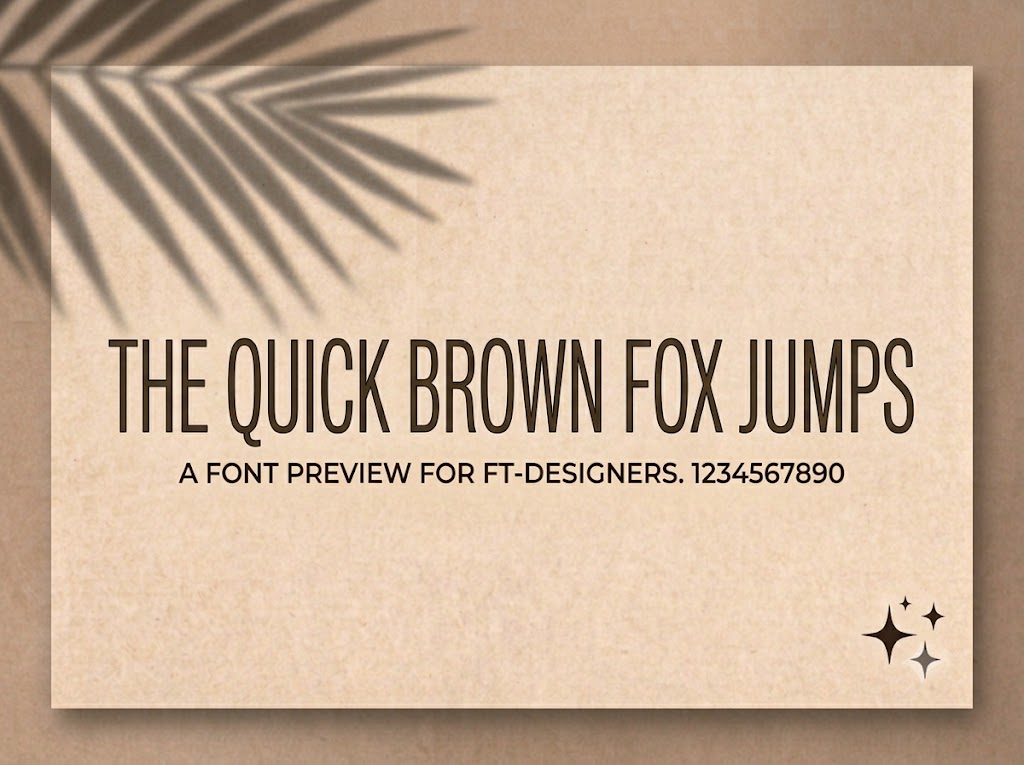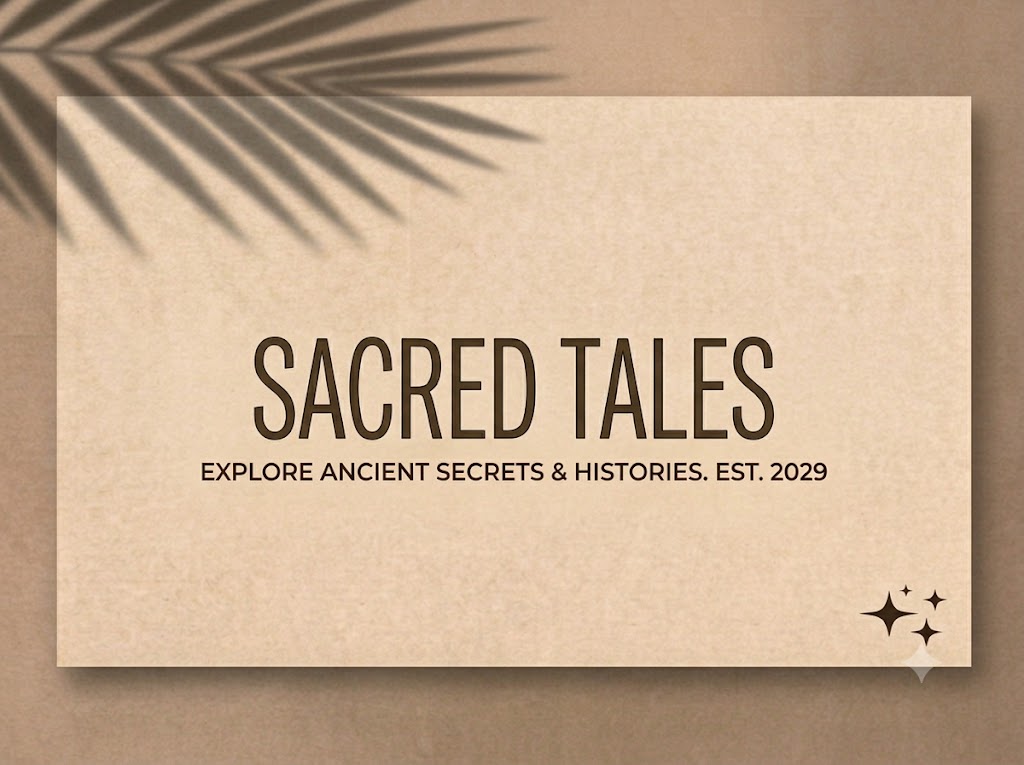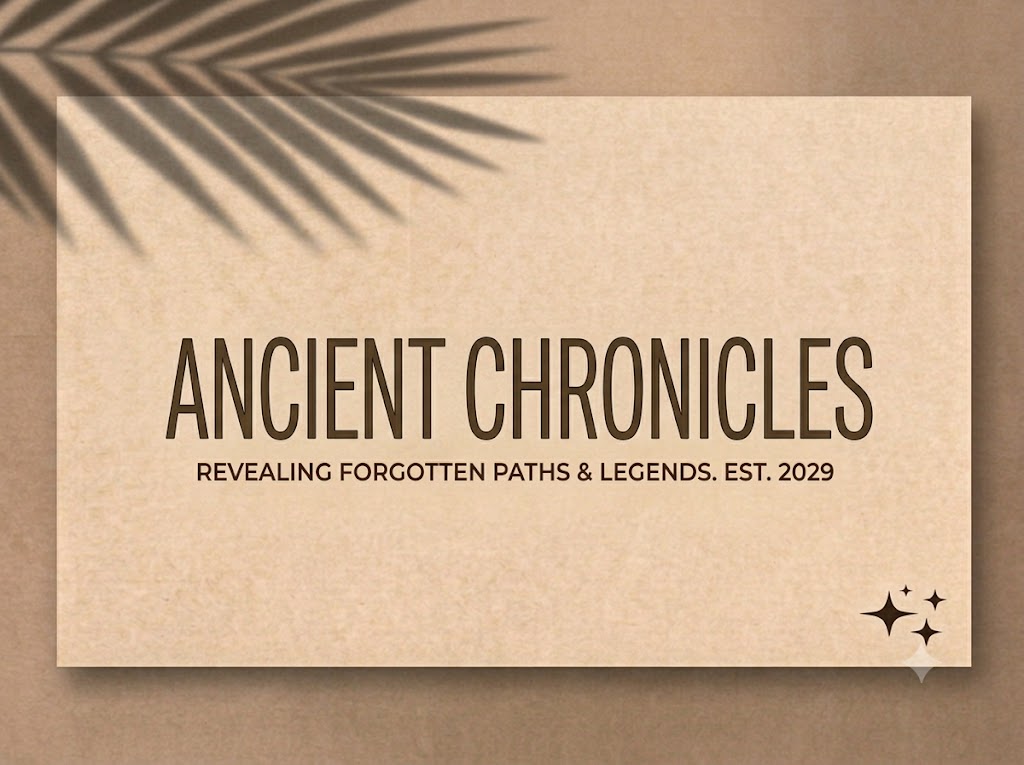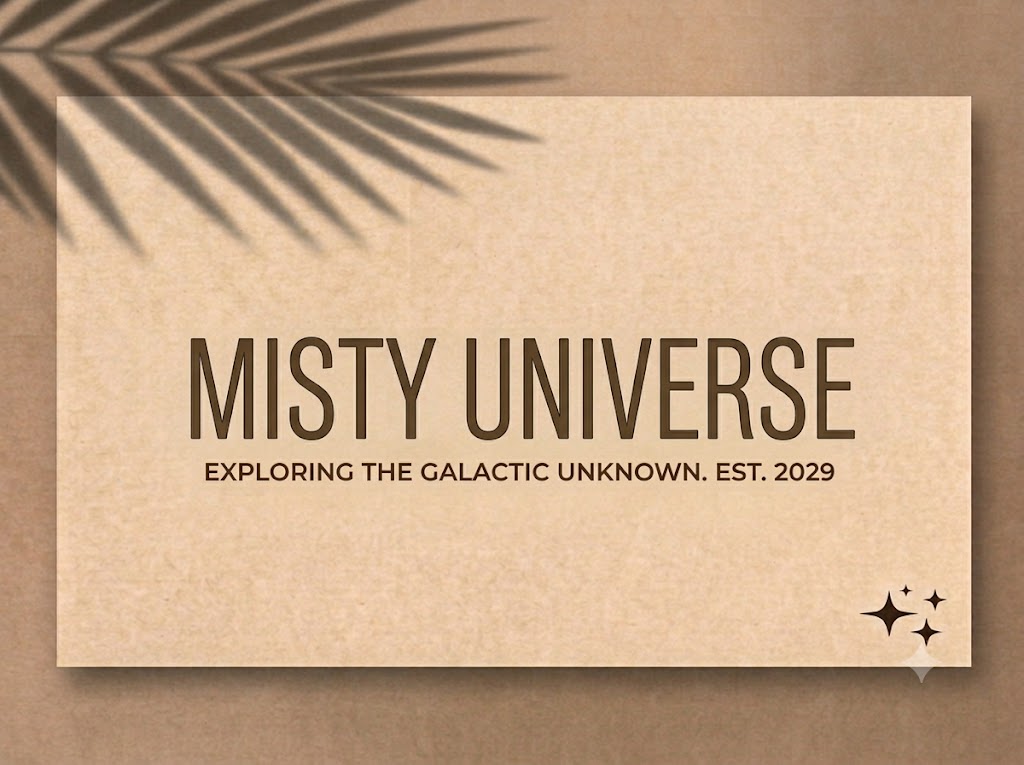
1FTV Retroyal
Trong kỷ nguyên sáng tạo nội dung số, việc tìm kiếm một phông chữ cân bằng được giữa nét cổ điển sang trọng và tính tối giản hiện đại luôn là ưu tiên hàng đầu.
Một kiểu chữ không chân (sans-serif) đứng dáng, sạch sẽ sẽ giúp tối ưu hóa thị giác và nâng cao trải nghiệm đọc của người xem trên mọi nền tảng hiển thị.
Nếu bạn đang tìm kiếm một bộ font đa năng để làm tiêu đề phim, thiết kế ảnh thu nhỏ mạng xã hội hay biên tập video truyền thông, thì font 1FTV Retroyal chính là giải pháp hoàn hảo.
Giới thiệu về font 1FTV Retroyal
Font 1FTV Retroyal là một bộ chữ thuộc thể loại display không chân mang phong cách thiết kế kết hợp tinh tế giữa hơi hướng hoài cổ (retro) và nét quý phái, thanh lịch (royal).
Nhờ những thông số kỹ thuật tối ưu này, phông chữ có khả năng hiển thị vô cùng sắc nét trên các phần mềm đồ họa chuyên nghiệp mà không lo gặp phải lỗi răng cưa khi phóng lớn bố cục. Được chia sẻ rộng rãi bởi đội ngũ 1FTV, đây là giải pháp typographic lý tưởng cho các designer và content creator tại Việt Nam.
Đặc điểm nổi bật của phong cách thiết kế Retroyal
Sức hút lớn nhất của font 1FTV Retroyal đến từ phom dáng đứng ngay ngắn, gọn gàng kết hợp với các tỷ lệ hình học cân đối một cách tinh tế.
Tuy thuộc nhóm font không chân mang tinh thần hiện đại, Retroyal vẫn phảng phất nét hoài cổ đầy chất thơ nhờ cách tạo hình các cung tròn thông thoáng ở những ký tự như o, e, c, a, g.
Bộ font hỗ trợ trọn vẹn cả hệ thống chữ cái viết hoa lẫn chữ viết thường đồng bộ, tạo điều kiện thuận lợi cho các nhà thiết kế tự do sắp xếp bố cục nhằm mang lại một nhịp điệu đọc tự nhiên và thoáng mắt nhất.
Độ dày nét chữ thuộc nhóm regular/medium vừa vặn, tạo cảm giác thanh thoát, dễ chịu cho mắt nhưng vẫn giữ được sự vững chãi cần có để làm nổi bật thông điệp truyền thông.
Để phông chữ vận hành hoàn hảo trên mọi hệ điều hành và phần mềm biên tập, phiên bản font 1FTV Retroyal đã trải qua quy trình xử lý thông số kỹ thuật nội tại vô cùng kỹ lưỡng.
Hệ thống khoảng cách chữ (kerning) và độ giãn dòng (tracking) đã được căn chỉnh chuẩn xác, giúp văn bản khi đứng cạnh nhau luôn đạt tỷ lệ vàng về mặt khoảng trống, không bị dính nét hay gây ngột ngạt cho người đọc.
Bên cạnh hệ thống chữ cái hoa và thường đồng bộ, font còn tích hợp đầy đủ dãy số từ 0-9 cùng hệ thống ký tự đặc biệt, dấu câu thông dụng (1234567890.:,;'"(!?)+-*/=).
Bản Việt hóa chuẩn chỉnh này đảm bảo các nhà sáng tạo có thể gõ nội dung tiếng Việt hoàn toàn mượt mà, tự nhiên mà không lo gặp phải tình trạng nhảy font hay lỗi hiển thị dấu câu khó chịu.
Hình ảnh demo thực tế của font 1FTV Retroyal
Để giúp bạn dễ dàng hình dung khả năng co giãn và hiển thị linh hoạt của phông chữ này trên các kích thước khác nhau, hãy cùng xem qua bảng mô phỏng từ file hệ thống:
Kích thước nhỏ (12pt – 24pt): Nhờ cấu trúc chữ đứng ngay ngắn và khoảng hở thông thoáng, các khối chữ viết thường vẫn hiển thị cực kỳ rõ ràng, sắc nét và dễ đọc ngay cả trên màn hình điện thoại di động cỡ nhỏ.
Kích thước lớn (36pt – 72pt): Đây là đất diễn lý tưởng nhất để font chữ phô diễn toàn bộ sự thanh lịch, tạo hiệu ứng thị giác hiện đại, chuyên nghiệp và ngăn nắp cho các dòng headline chính.
Ứng dụng của font Retroyal trong thiết kế đồ họa và làm video
Sở hữu nét cá tính thanh lịch, hoài cổ và cấu trúc hoa – thường linh hoạt, font 1FTV Retroyal mở ra không gian ứng dụng vô cùng rộng lớn cho các dự án truyền thông và marketing hiện đại:
Làm tiêu đề và phụ đề video ngắn (TikTok, Reels, Shorts): Dáng chữ đứng, gọn gàng và thanh thoát cực kỳ hoàn hảo cho các khung hình dọc 9:16, giúp lời thoại phụ đề rõ ràng, tự nhiên và cuốn hút người xem lướt qua feed mà không che mất chủ thể chính của video.
Thiết kế ảnh thu nhỏ mạng xã hội (Thumbnail): Lựa chọn tuyệt vời cho các thumbnail YouTube, TikTok quảng cáo sản phẩm, giáo dục hoặc chia sẻ phong cách sống nhằm tăng tỷ lệ nhấp chuột nhờ độ hiển thị trực diện, dễ đọc từ khoảng cách xa.
Banner và poster quảng cáo e-commerce: Hoàn hảo cho các poster giới thiệu sản phẩm thời trang, mỹ phẩm, trang sức, hoặc các chiến dịch marketing kỹ thuật số đòi hỏi sự tinh tế, súc tích nhưng vẫn giữ được vẻ sang trọng.
Nhận diện thương hiệu phong cách tối giản: Phù hợp làm logo dạng chữ khối, biểu ngữ quảng cáo hoặc thiết kế nhãn mác cho các thương hiệu local brand, tiệm cà phê, hoặc các studio sáng tạo trẻ tuổi hướng tới sự tinh tế, bền vững.